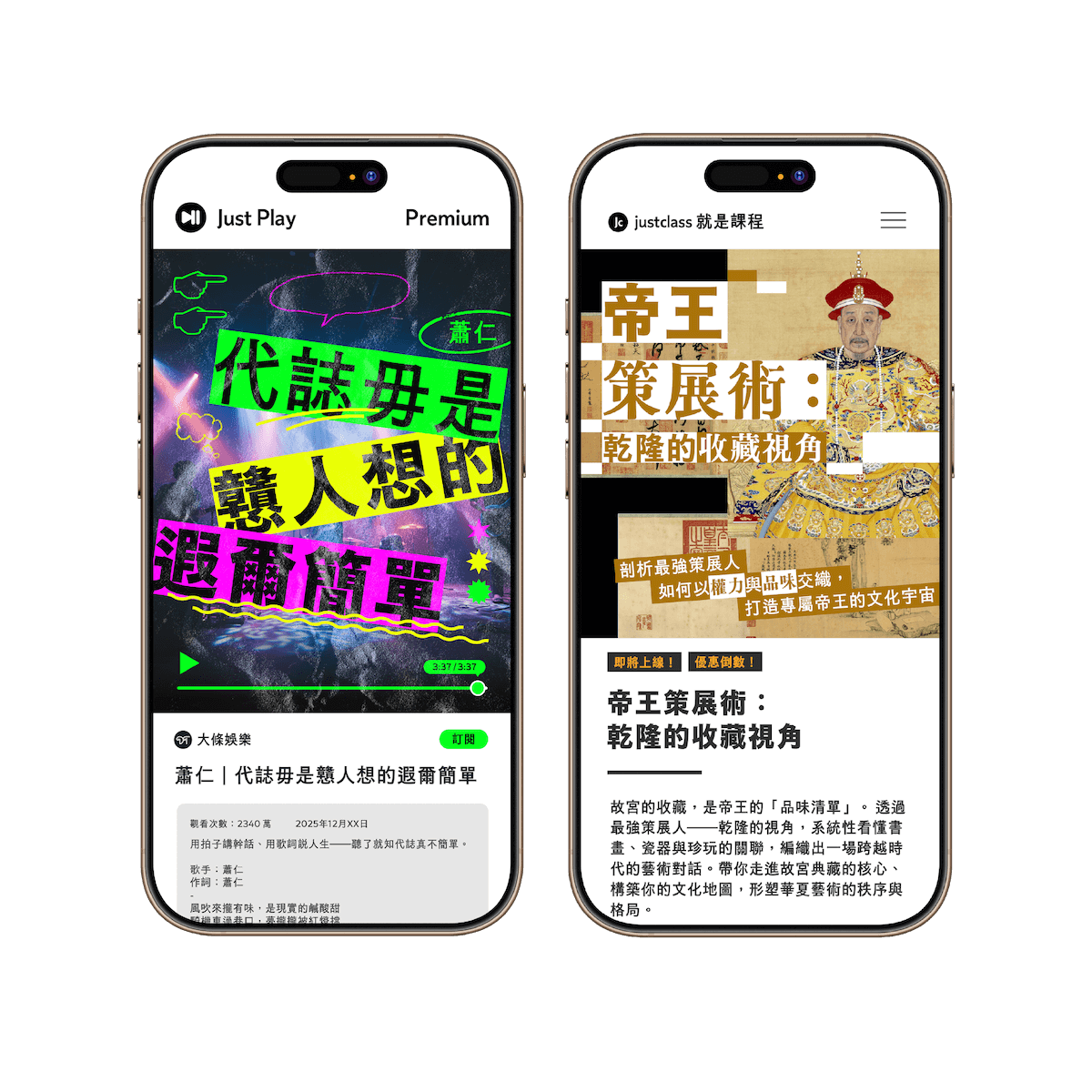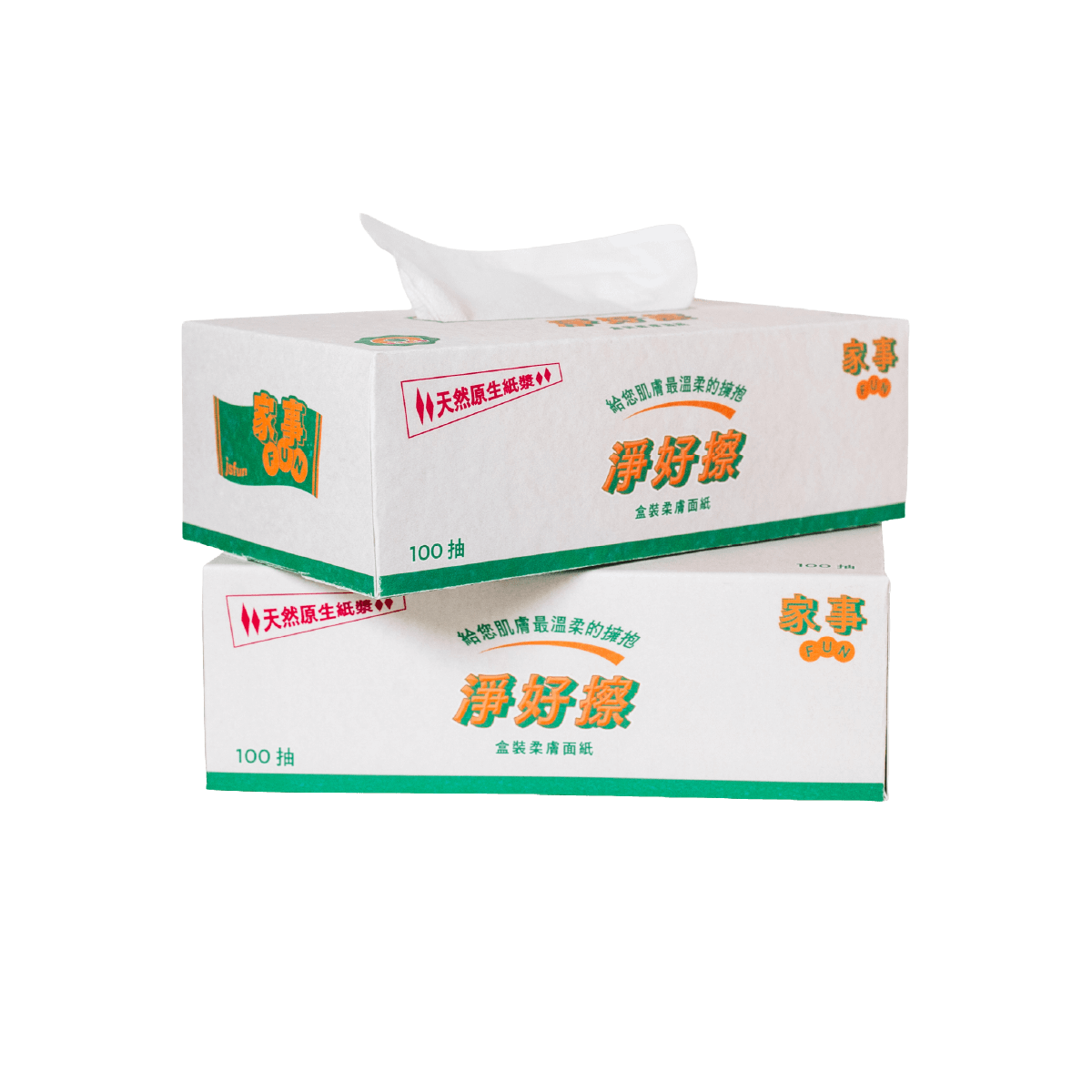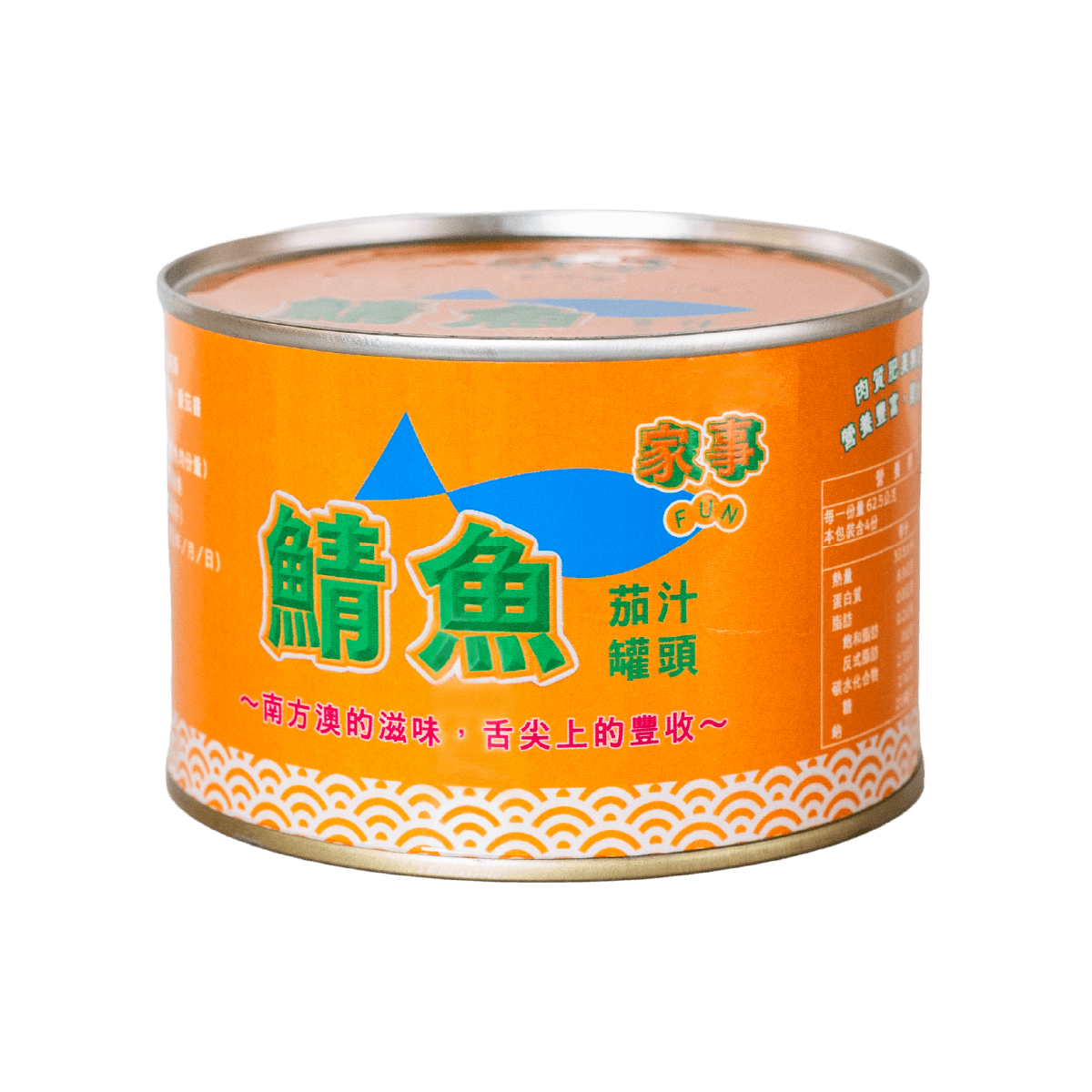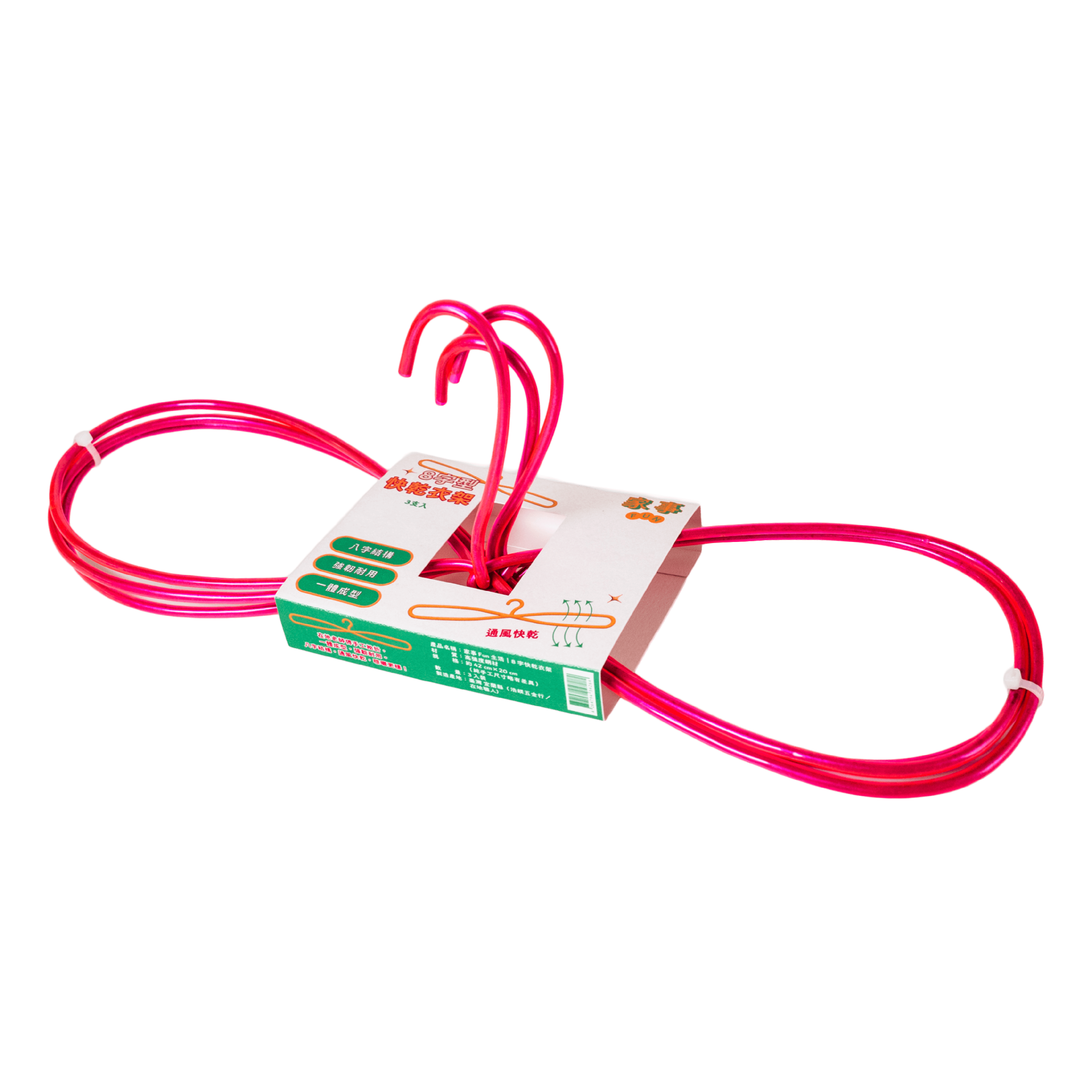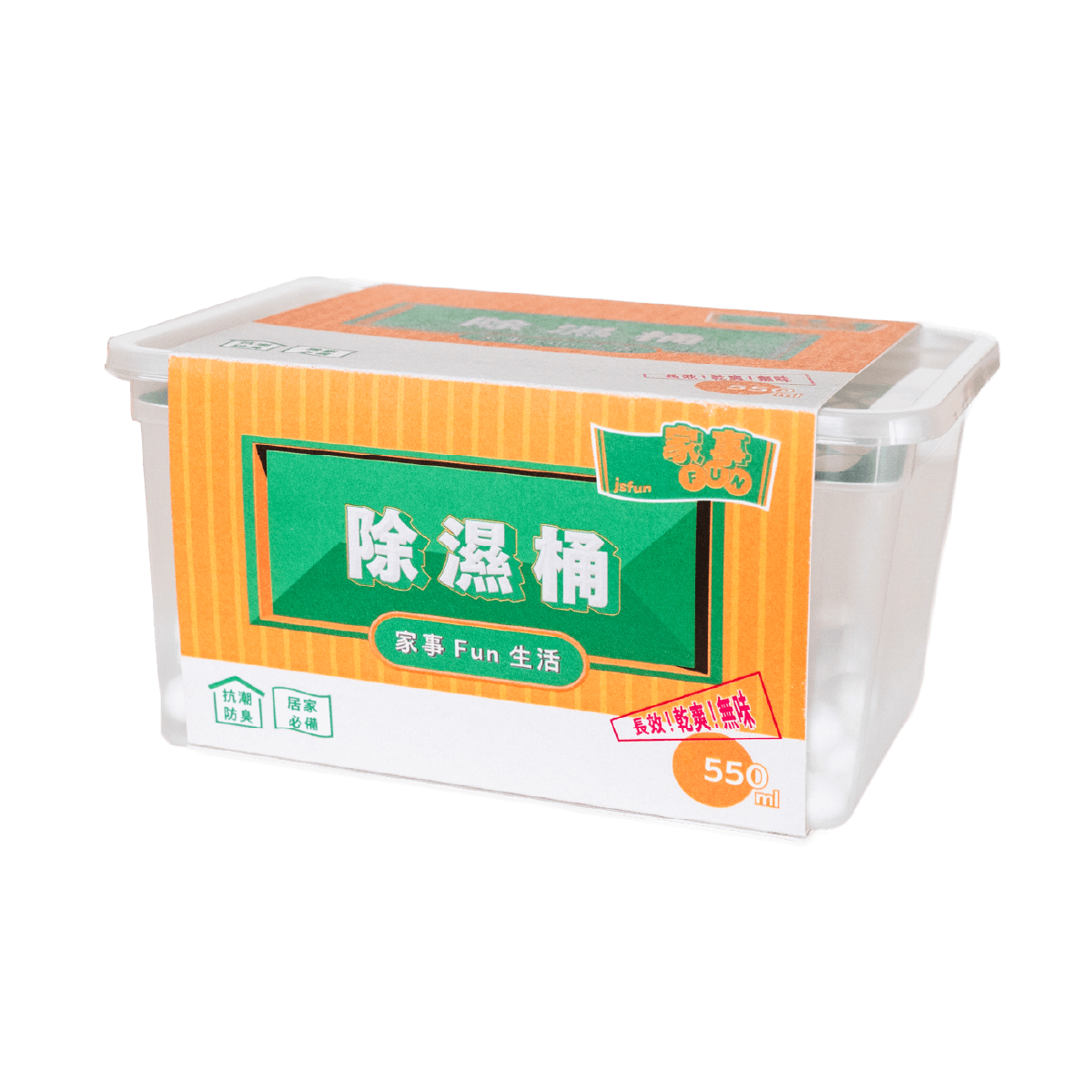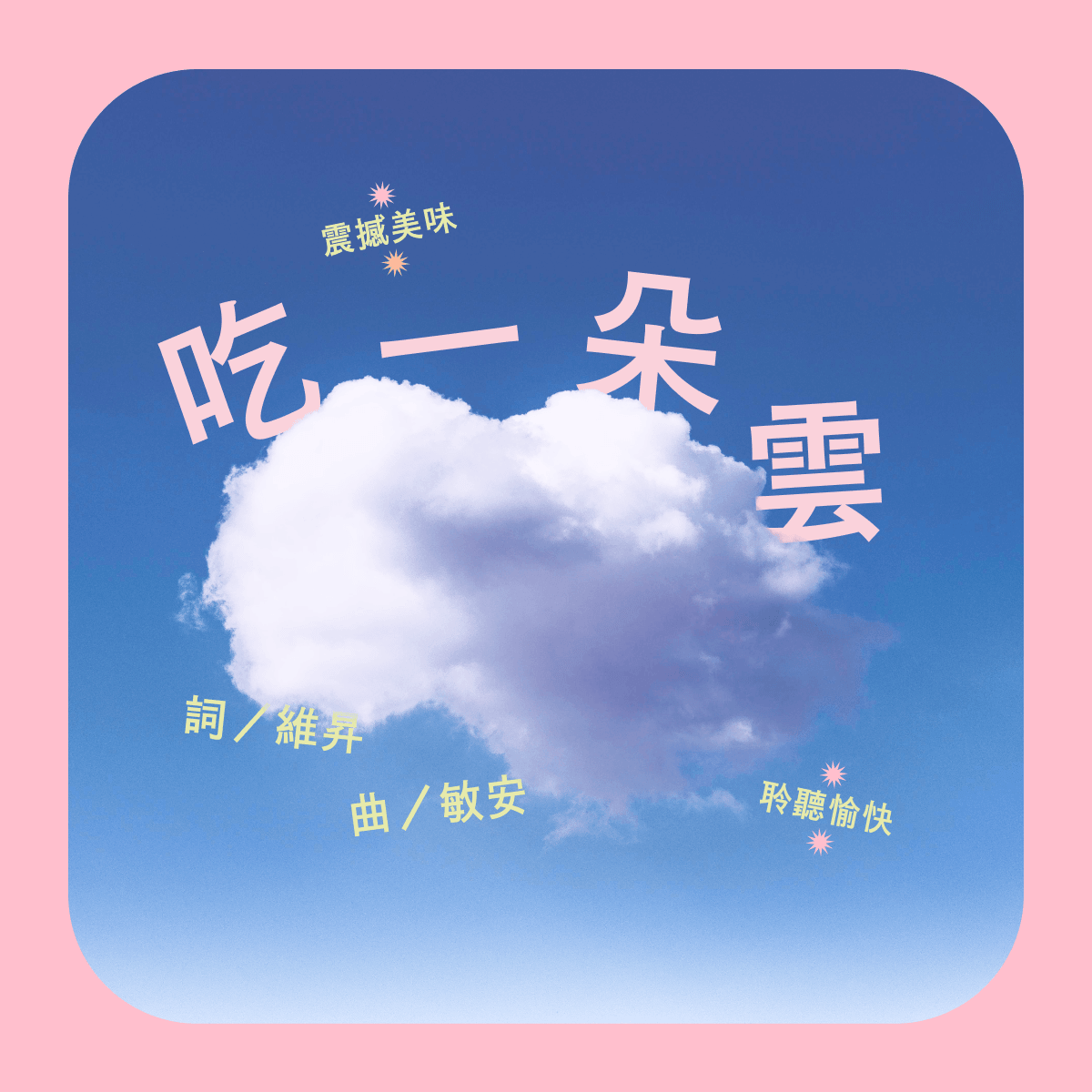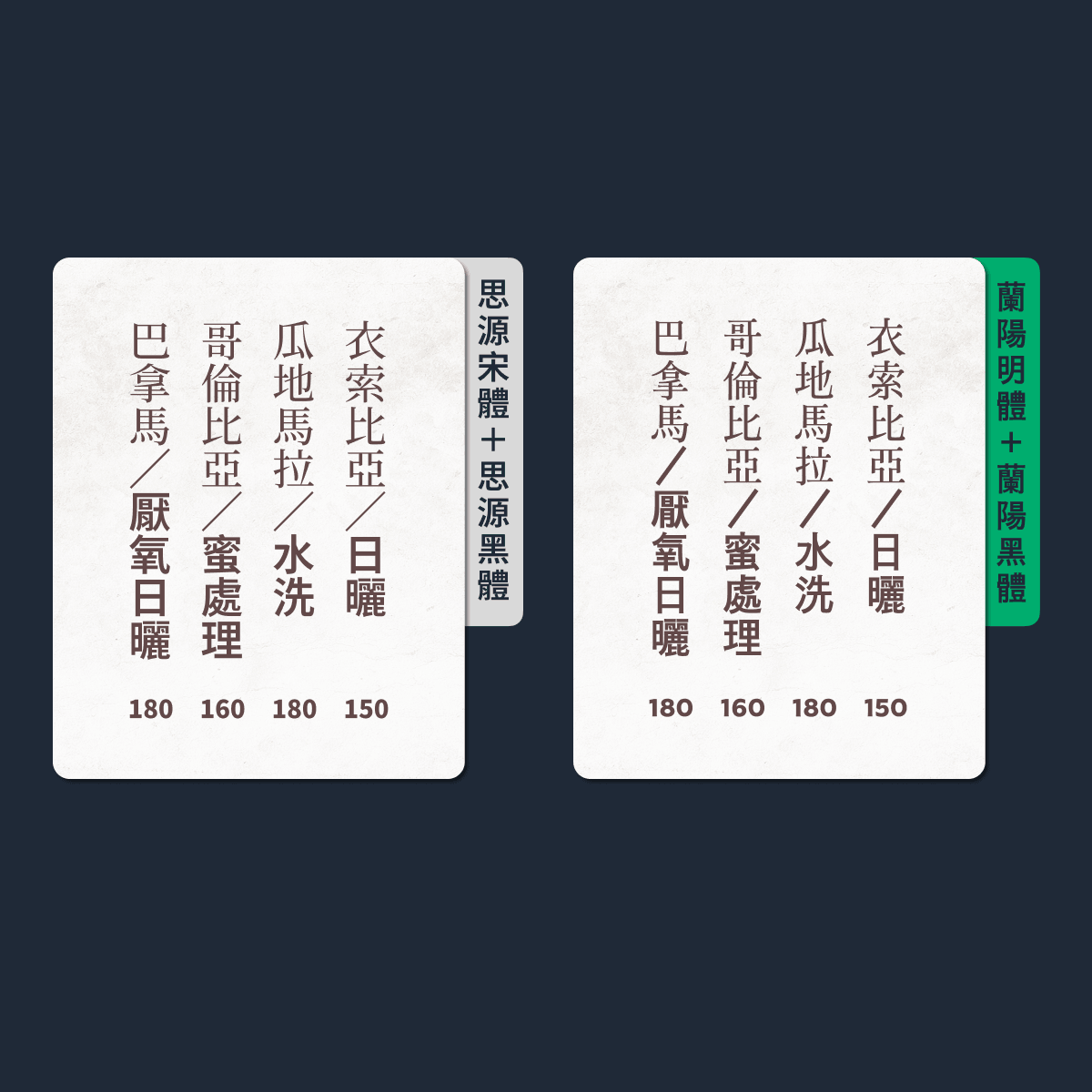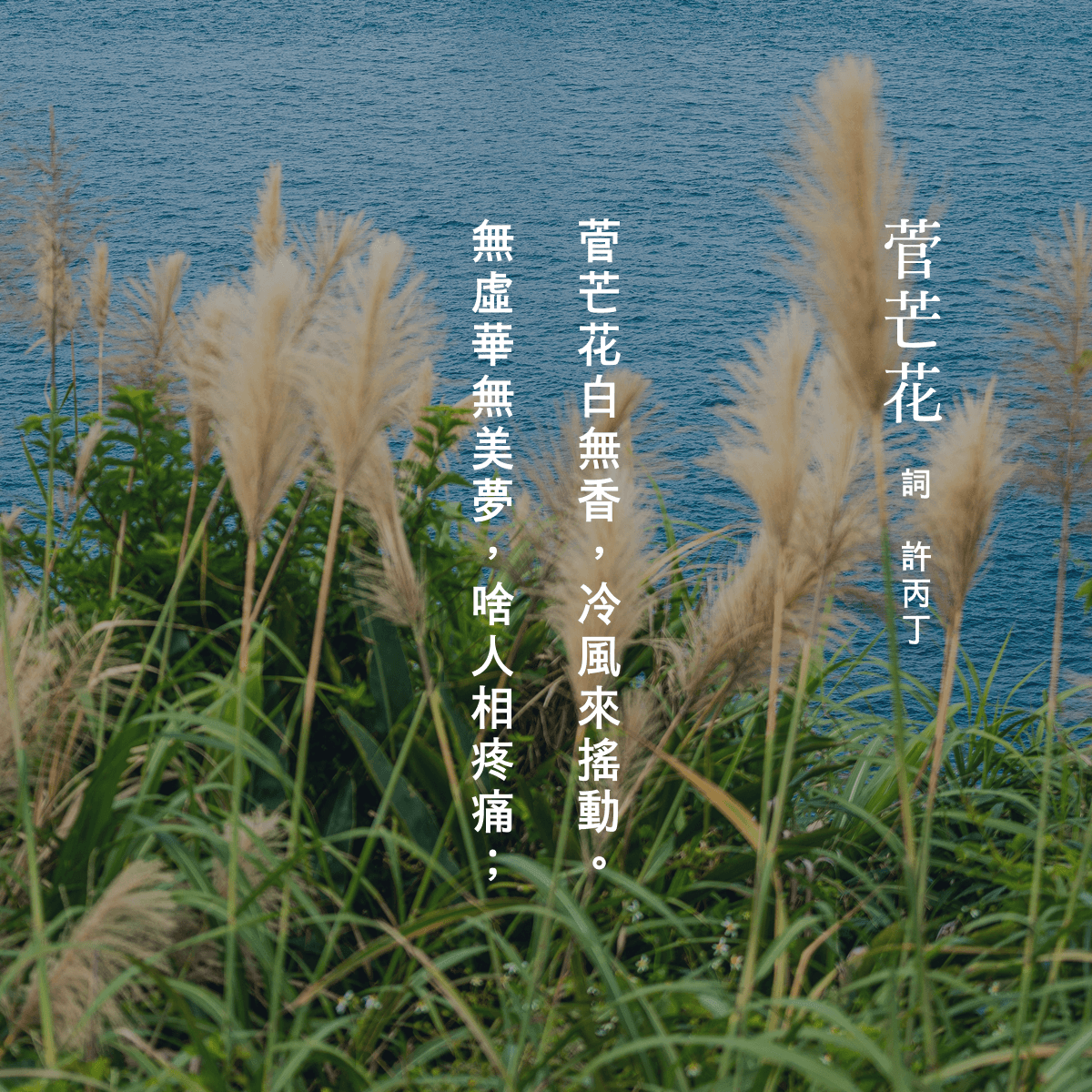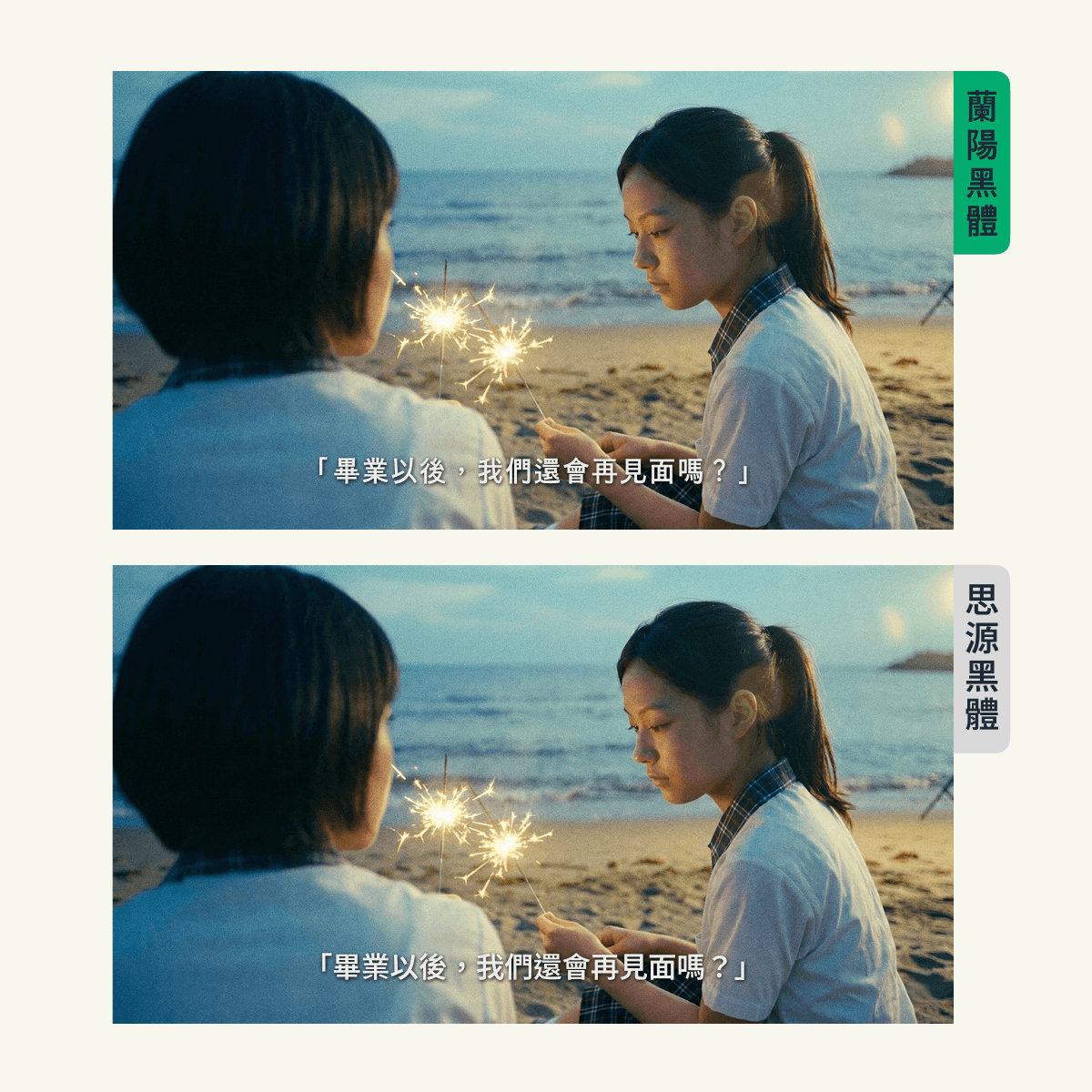
jf 蘭陽黑體
justfont 字型總監林霞繼蘭陽明體之後又一力作,蘭陽黑體的特色是靈活多變,保留文字天然形狀與動感。擺脫黑體千篇一律的刻板印象。婀娜多姿人情味,讓你創造更有意思的視覺表達。
字型設計師
林霞
宜蘭人,justfont 字體總監,30 年字體設計經驗。催生金萱、金萱那提與蘭陽等字型系列,並在凝書體、激燃體與臺灣道路體創作過程中擔任總顧問。喜歡開車。每天一號表情盯著螢幕,幻想著今天到印度,下一站到歐洲,然後再計劃到南美洲,環遊世界。